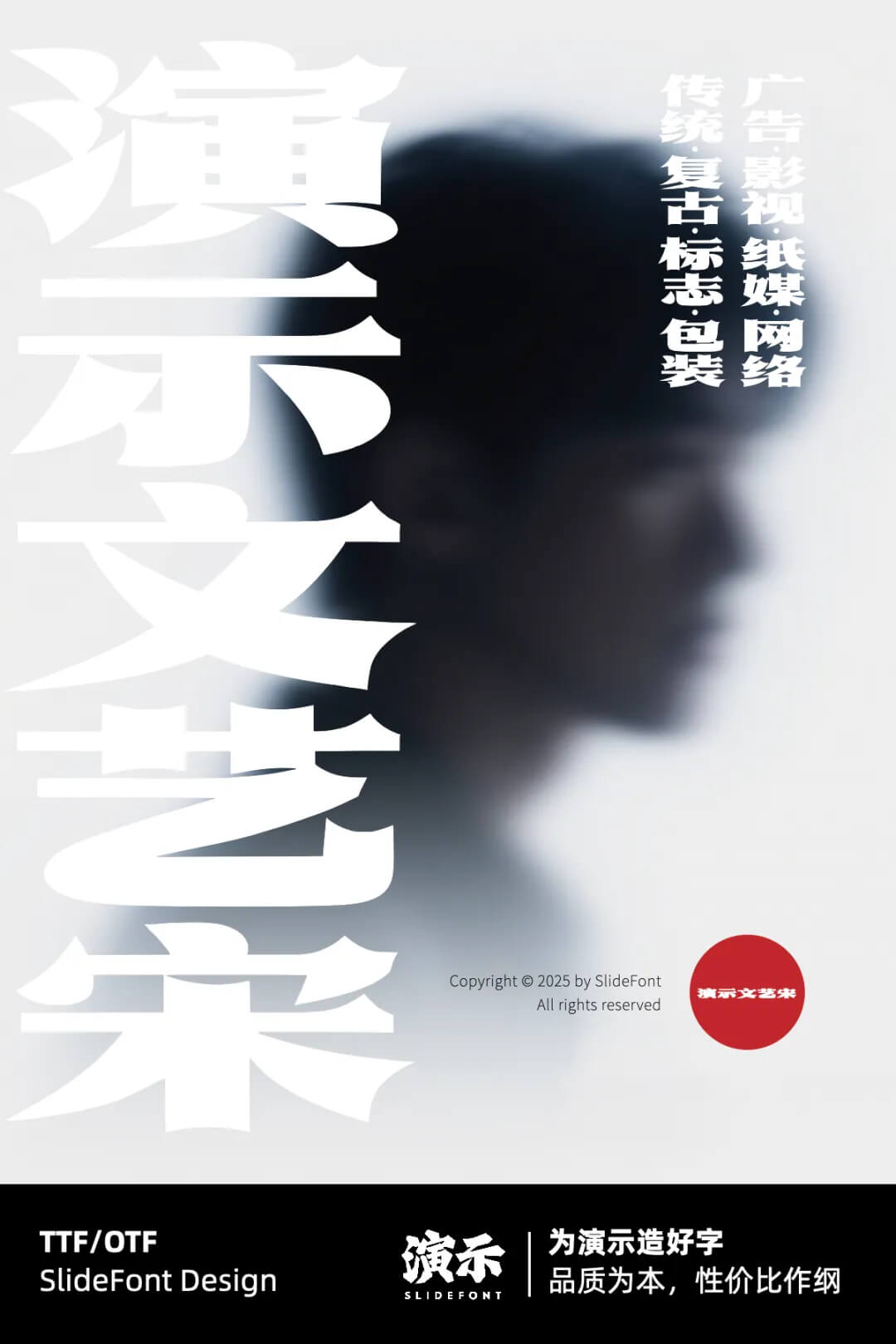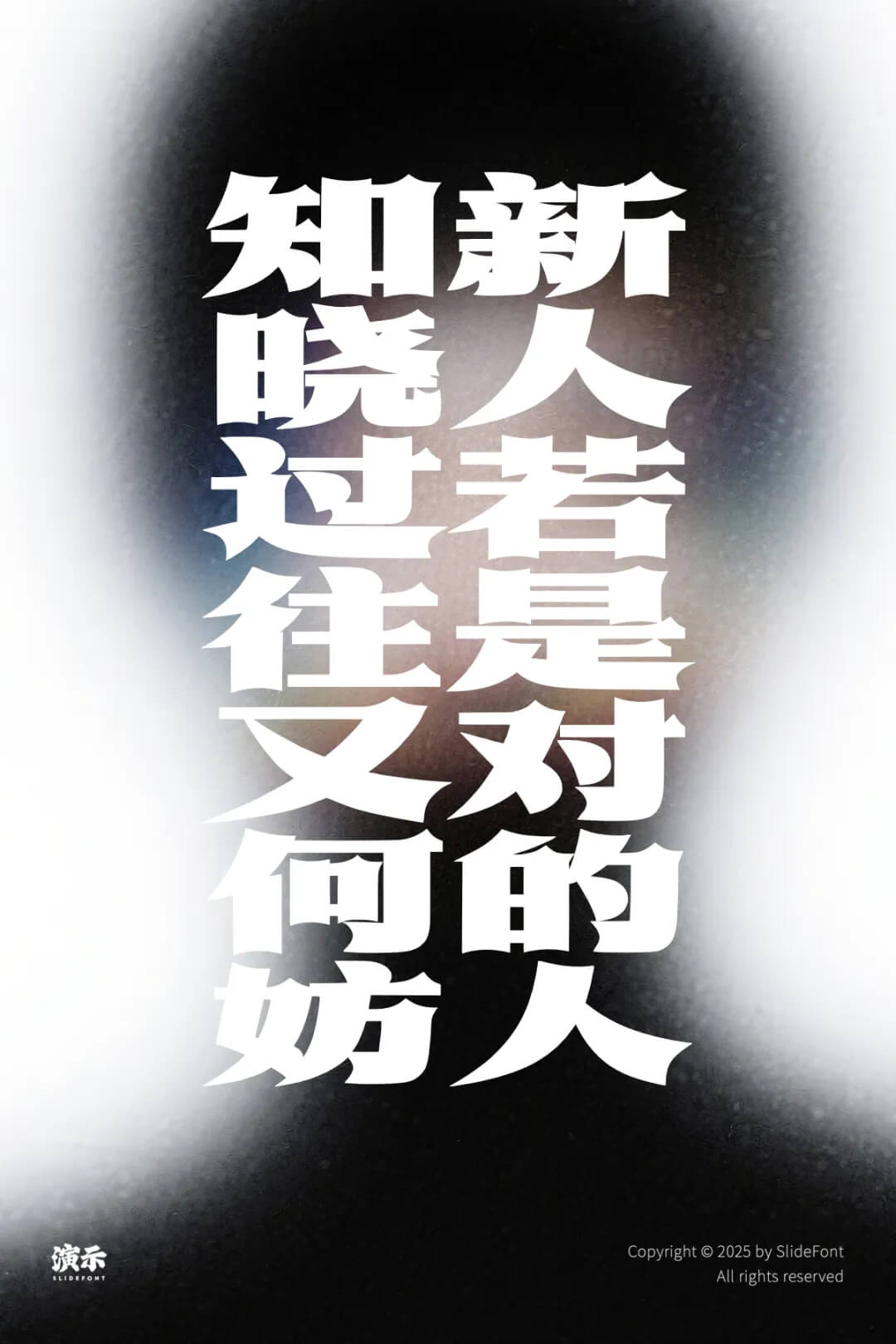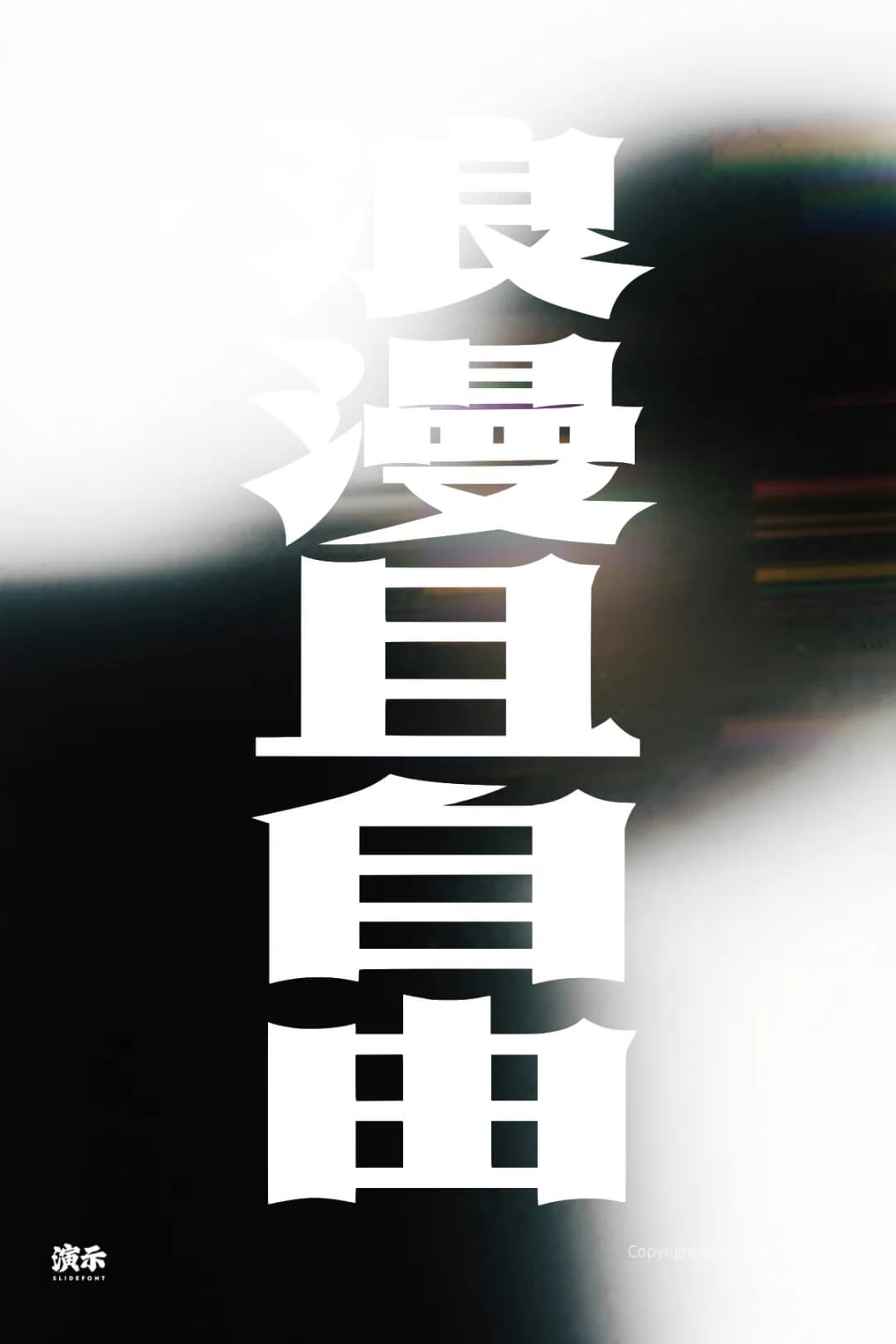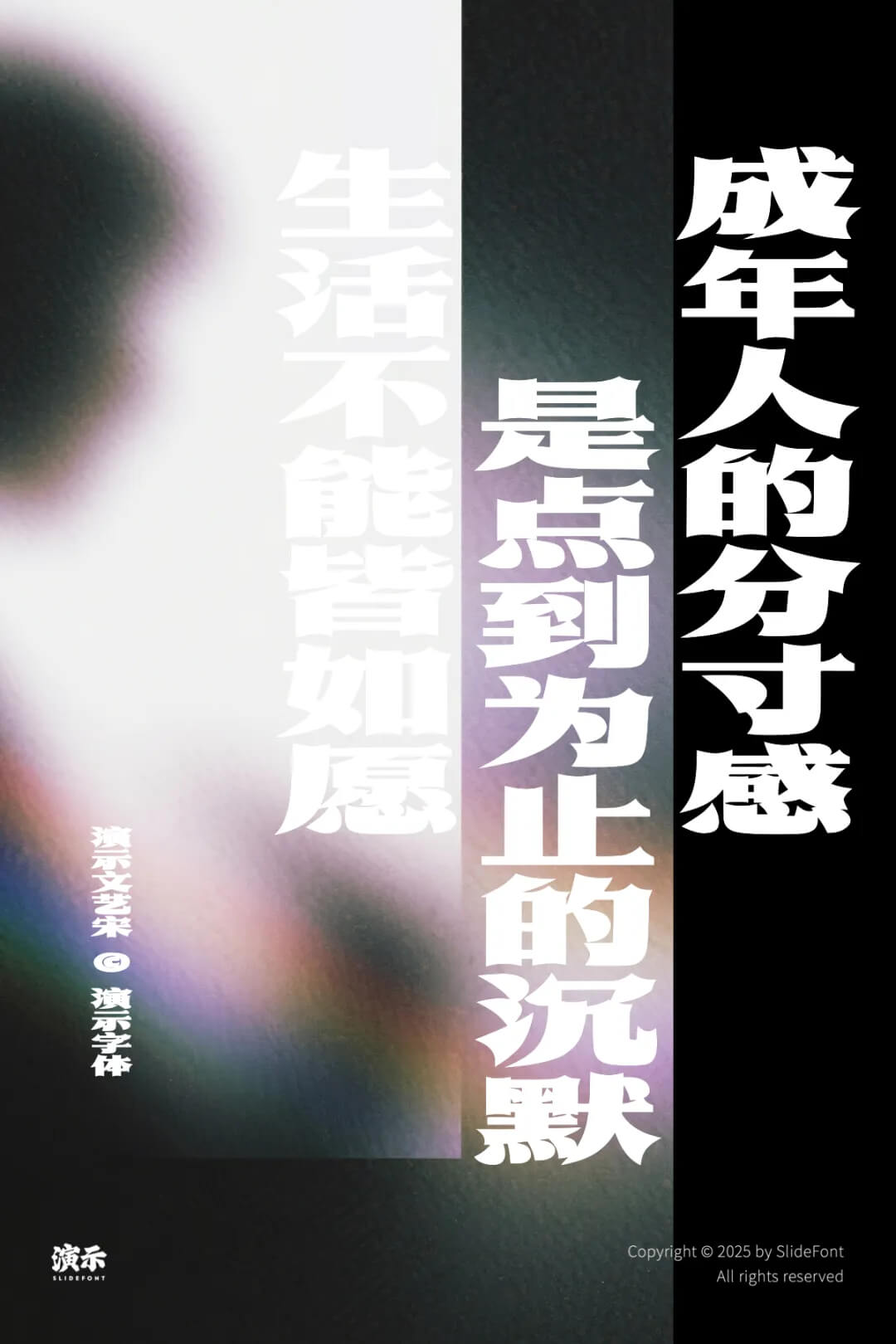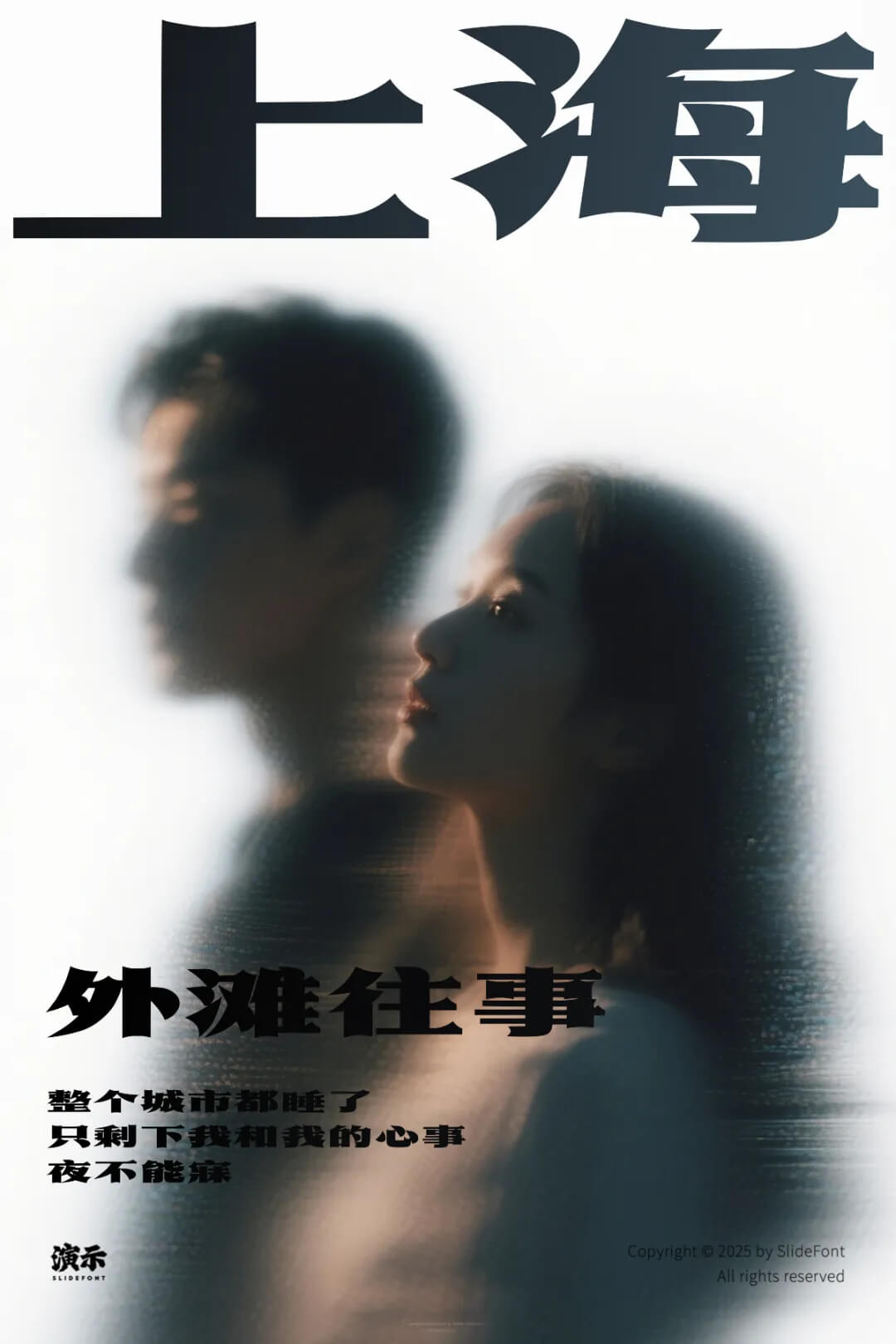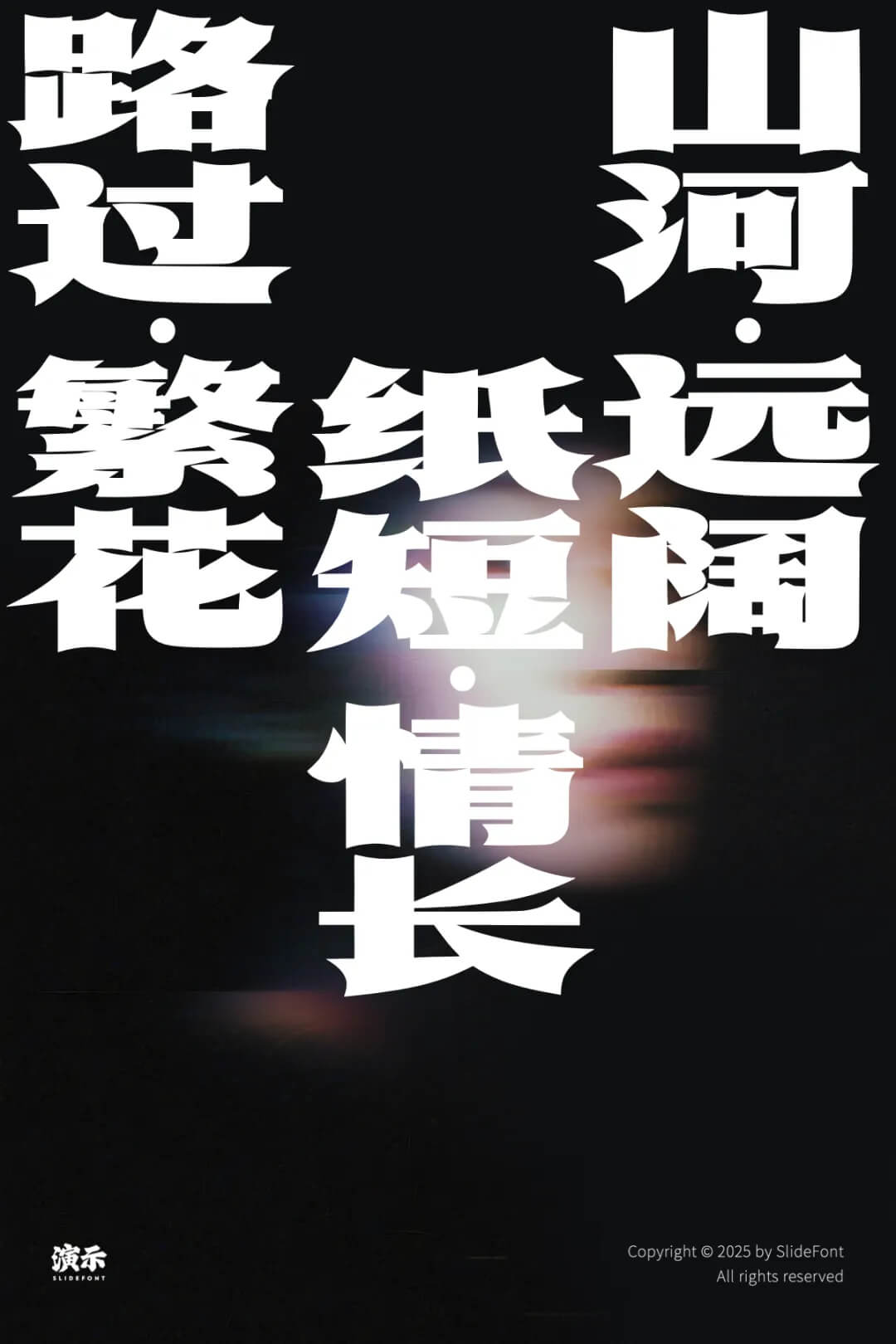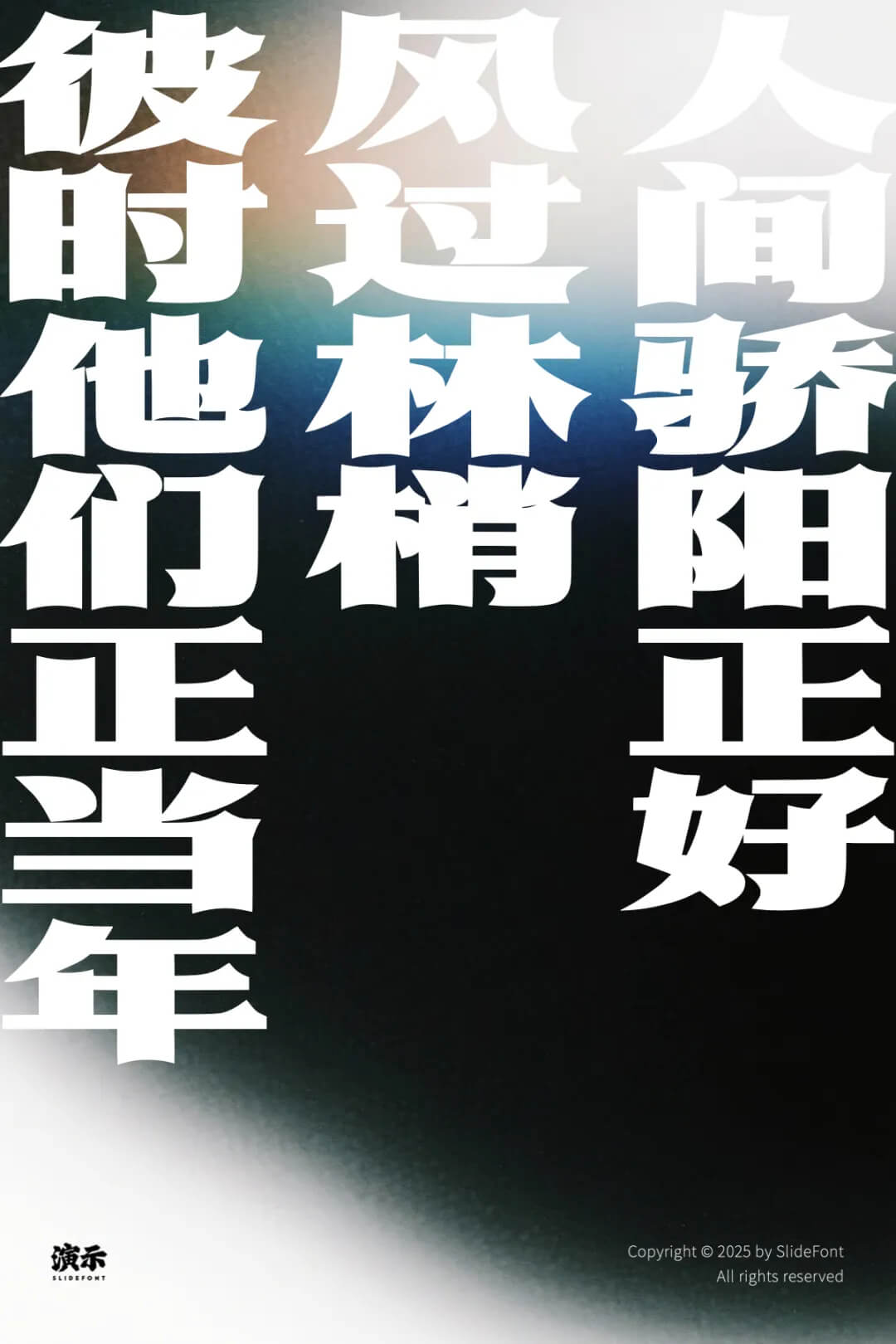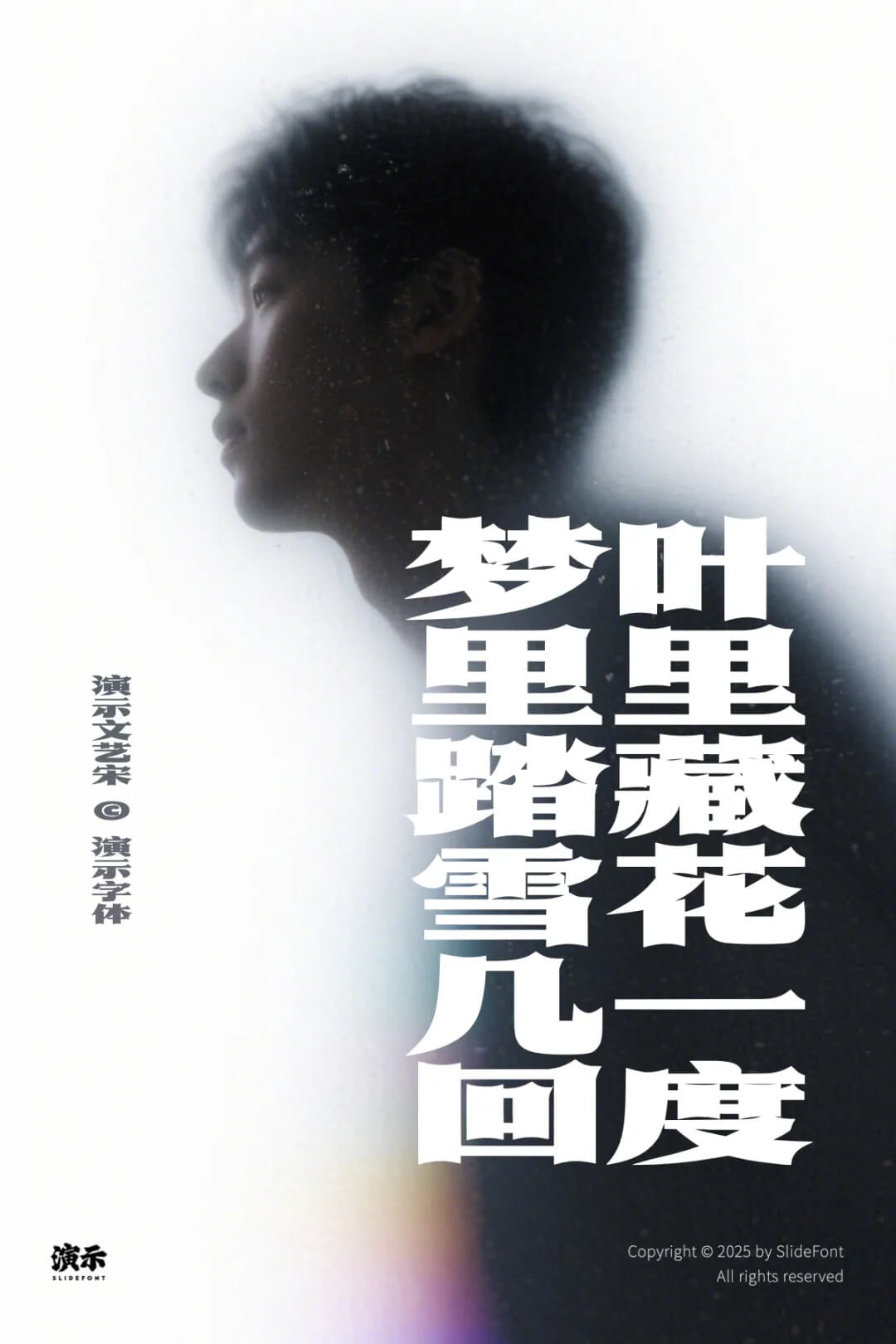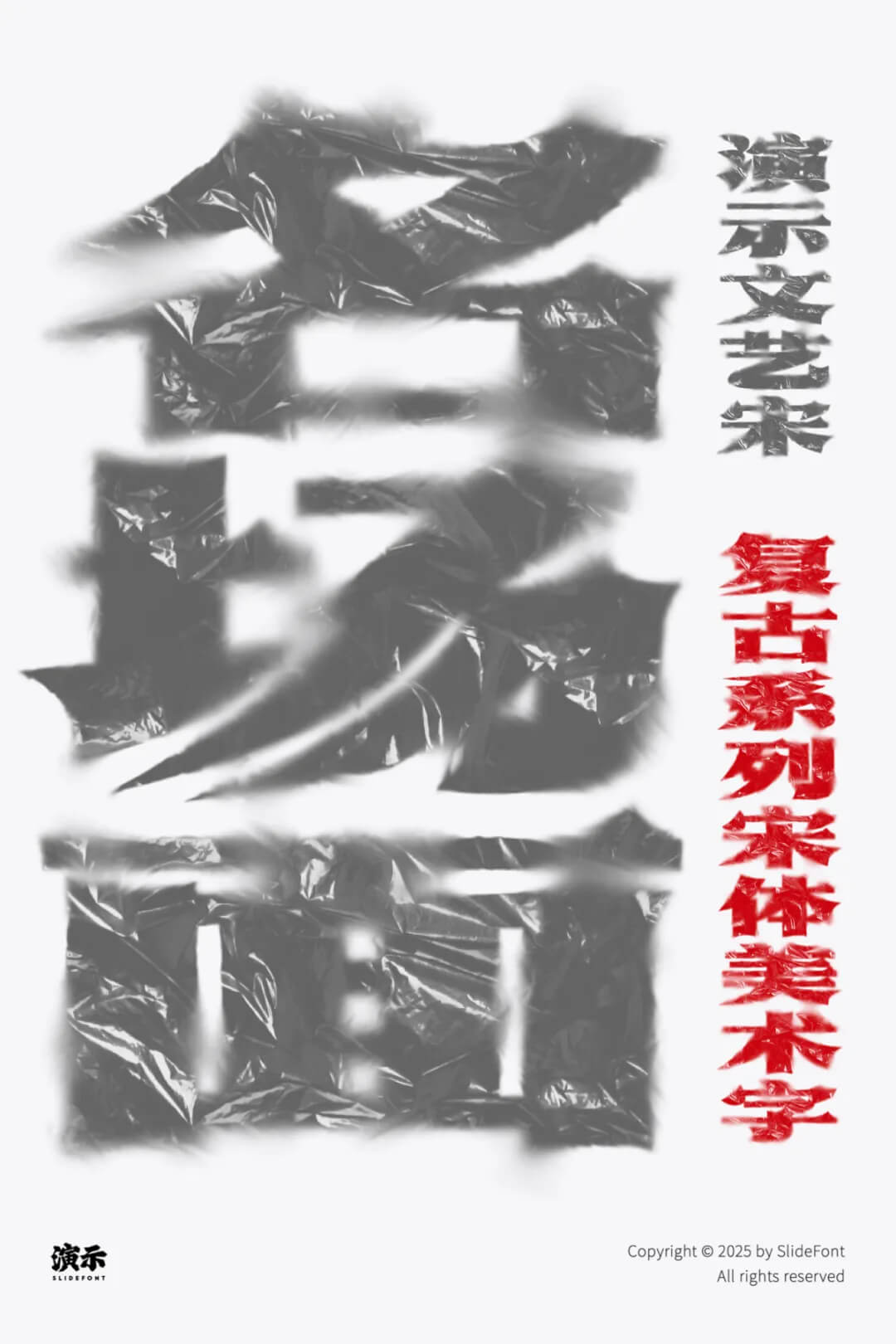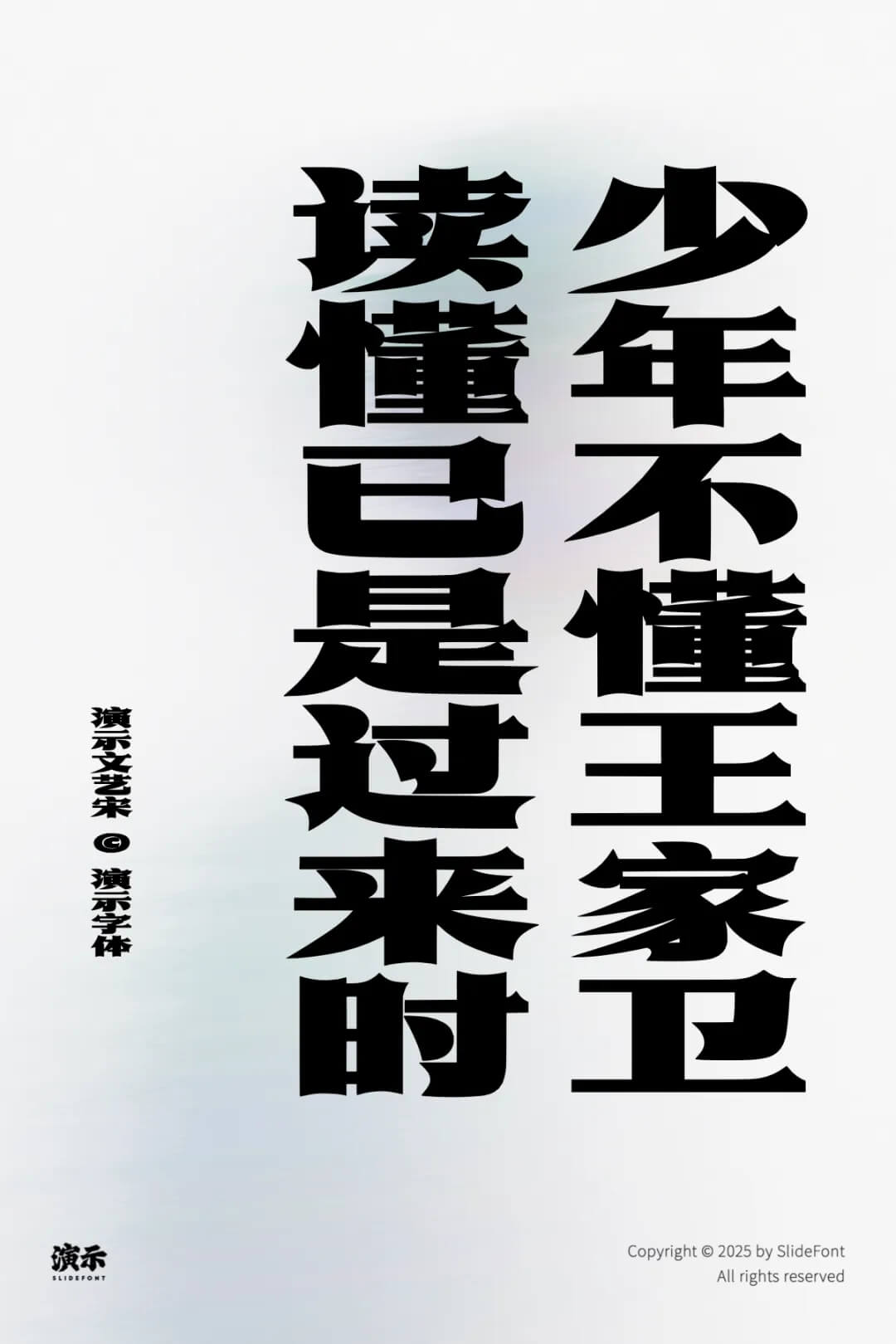
演示文艺宋
演示文艺宋是演示字体推出的创意宋体美术字。其灵感源自1947年作家书屋刊行、冯玉祥所著的《我的读书生活》封面标题字。该字体字形宽扁10:18,极具民国时期书籍封面设计风格,装饰性与力量感十足。它横细竖粗对比强烈,横画收笔顿笔醒目,古朴韵味尽显;撇捺舒展流畅,收尾锐利却是对字形做了视觉补偿。这些特点使字体醒目且富有视觉冲击力,能快速吸引目光。报宋整体风格端庄稳重又不失灵动,庄重架构搭配舒展笔画,适用于大型活动标题、庄重宣传海报、书籍封面、演示文稿等需突出重点、营造正式氛围的场景 。
字体风格:创意美术字
字库标准:满足 GB2312-80 简体 + 多文种匹配
开发时间:2025.02